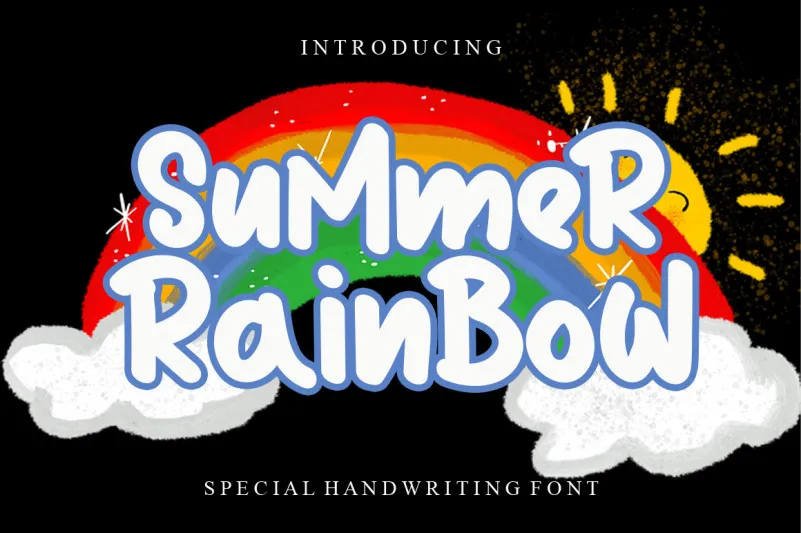
Summer Rainbow Font – Download Grátis
Esta fonte está disponível nas categorias Display Fonts, criada por LevinCreative. Ela é uma tipografia escrita a mão com traços fortes e amigáveis, ideal para destacar suas ideias de forma ainda mais realista e criar designs impressionantes. Perfeita para designers que buscam adicionar um toque personalizado em seus projetos gráficos ou web. Composta por LevinCreative, essa fonte é uma opção versátil para qualquer projeto que você possa imaginar. Aproveite esta oportunidade única para revolucionar a forma como suas ideias são transmitidas visualmente!